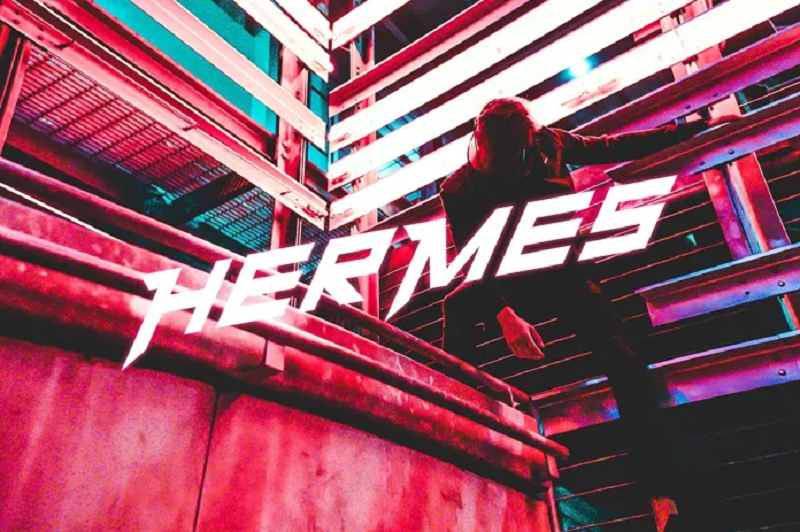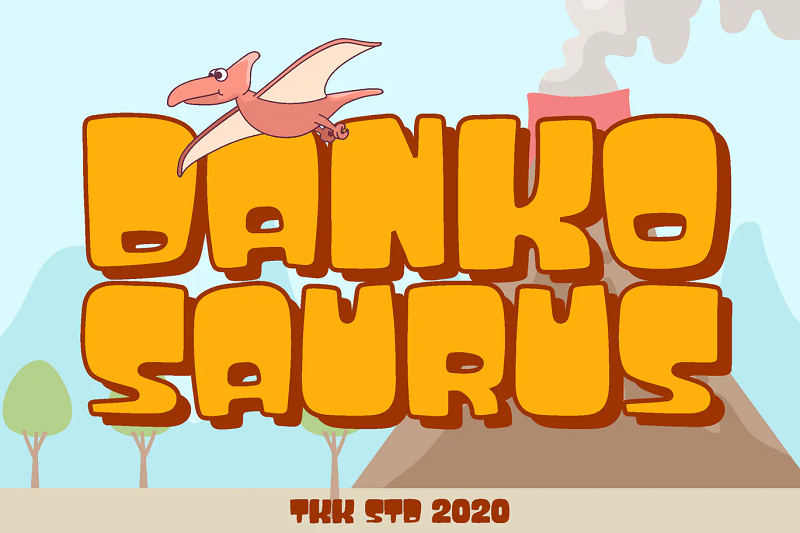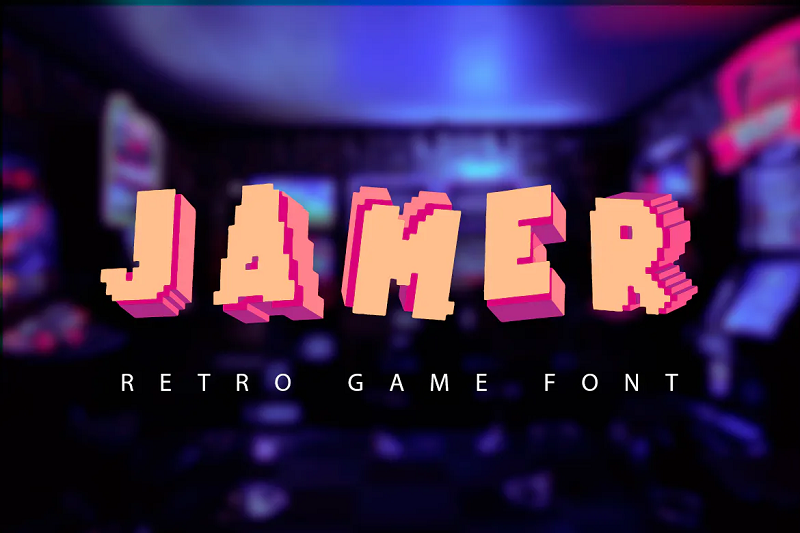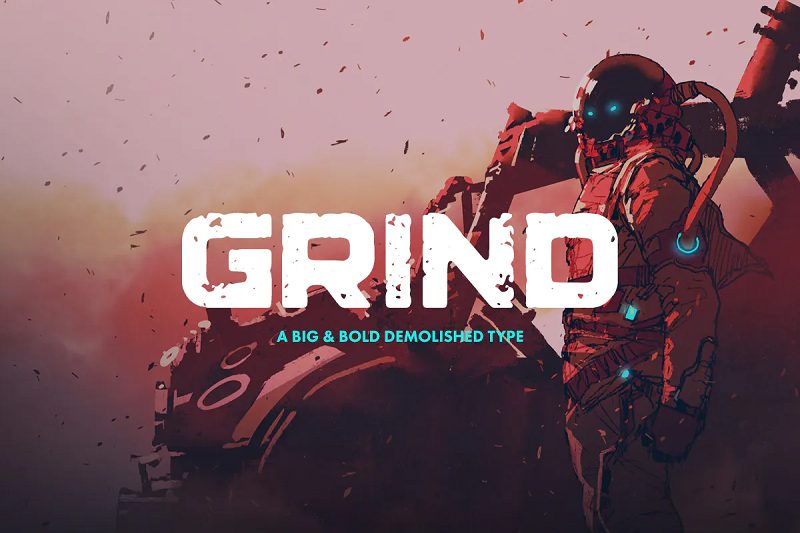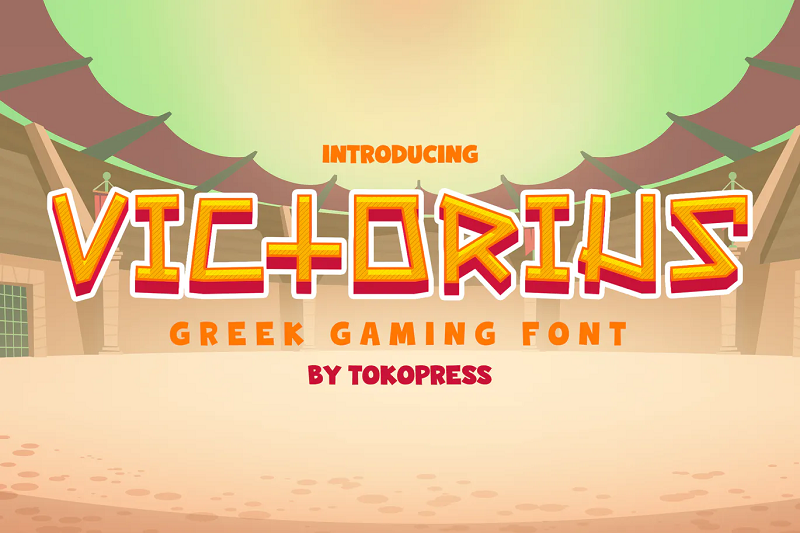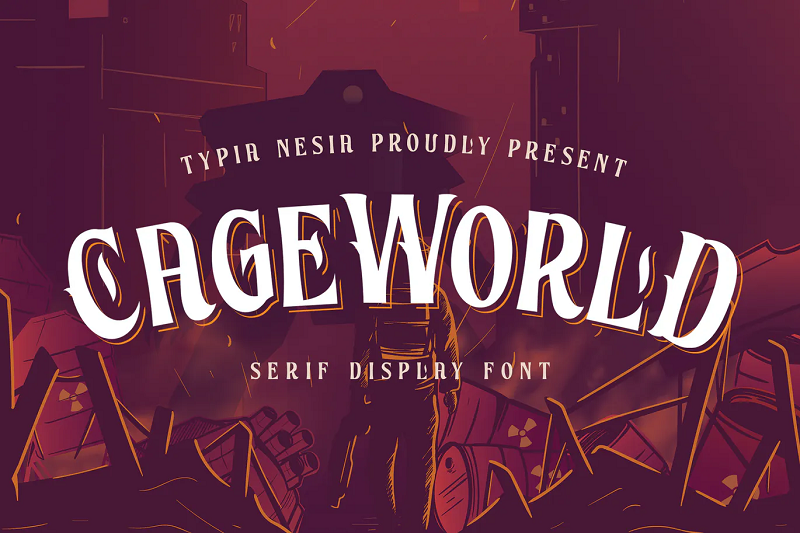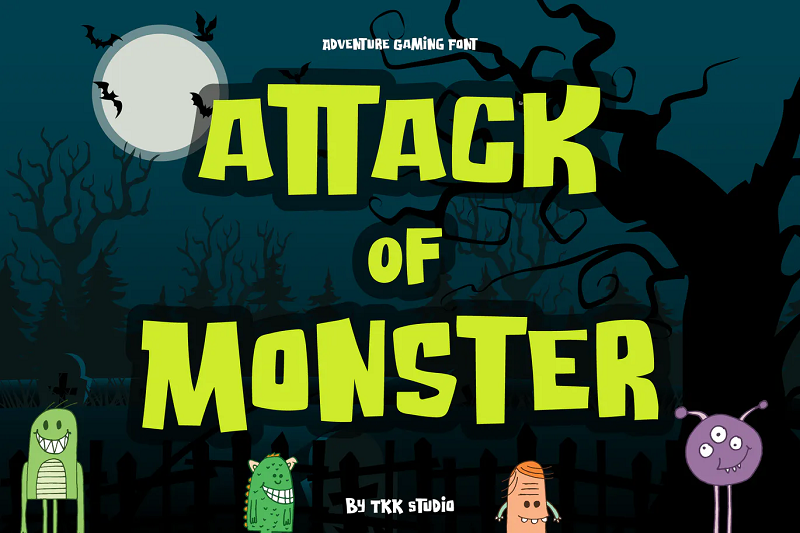
40 Font Game Terbaik Untuk Semua Desain Terkait Game Anda (2023)
Diterbitkan: 2023-01-03Seperti yang kita semua tahu, gamer memiliki selera gaya artistik yang unik. Jika Anda ingin memanfaatkan estetika permainan itu dan membuatnya kembali dalam proyek kreatif Anda sendiri, Anda memerlukan font yang tepat untuk pekerjaan itu.
Dengan mengingat hal itu, kami telah menyusun daftar font game terbaik yang tersedia pada tahun 2021. Tipografi di bawah ini cocok untuk desain terkait game apa pun.
Apakah Anda seorang pengembang video game yang mencari font keren untuk digunakan dalam proyek terbaru Anda, seorang pemasar yang mengerjakan branding/materi promosi game, atau streamer Twitch/pemain game YouTube yang mencari jenis huruf menarik untuk digunakan dalam sampul saluran Anda, Anda Anda pasti akan menemukan font yang Anda sukai di daftar ini.
40 font game terbaik
1. Font Permainan Video
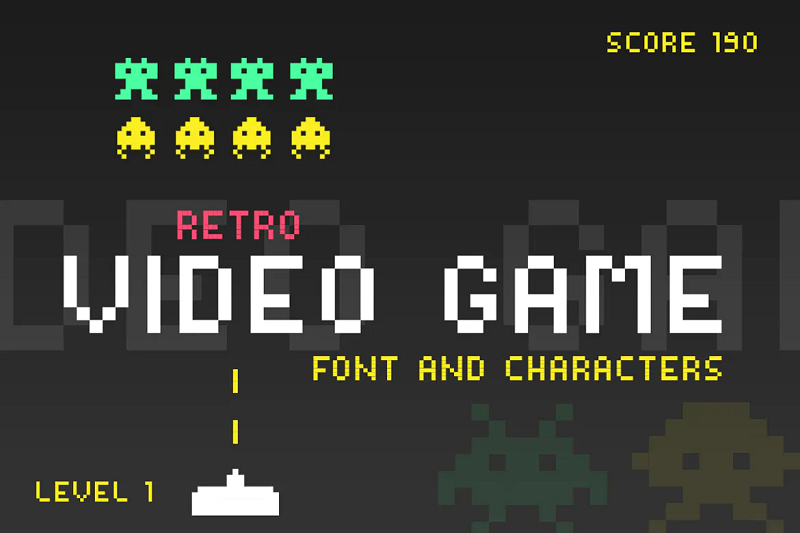
Mari kita mulai dengan ledakan ke masa lalu dengan 'font video game' yang terinspirasi gaya retro. Ini adalah desain yang memberi penghormatan pada game arcade klasik seperti penembak Mars favorit semua orang dari tahun 80-an, penyerbu luar angkasa. Ini sangat nostalgia.
Ini memiliki desain pixelated dan unduhan dilengkapi dengan set karakter utama dan 17 bonus pixelated martians, sehingga Anda dapat menambahkan beberapa grafik 8-bit yang keren ke desain Anda.
2. Jenis Huruf Tsuki
Tsuki adalah salah satu font sans-serif favorit pribadi saya sepanjang masa. Jenis huruf yang indah ini penuh dengan karakter. Ini terinspirasi oleh Manga Jepang dan akan terlihat bagus di JRPG dan game indie.
3. Game Over Font
Game Over adalah kuas buatan tangan dan font SVG. Desain sapuan kuas itu akan terlihat bagus dalam game horor, grunge, dan proyek artistik lainnya. Seperti namanya, itu juga akan berfungsi dengan baik sebagai teks 'game over' dalam game.
4. GUMDROP
Gumdrop adalah font yang menyenangkan, unik, dan modern yang bagus untuk game seluler. Ini adalah font kotak-kotak yang melompat dari halaman, sehingga akan bekerja dengan baik pada judul, poster, ikon YouTube, logo aplikasi android/ios, dan banyak lagi. Set termasuk karakter AZ dasar dalam huruf besar dan kecil, angka, dan tanda baca. Ini sepenuhnya kompatibel dengan Adobe Illustrator dan Photoshop.
5. Font Permainan Caveman
Seperti namanya, Caveman adalah font yang sepertinya berasal dari periode paleolitik. Ini sempurna untuk judul game bertahan hidup dan game apa pun yang dibuat di era kuno / Jurassic. Ini adalah jenis huruf yang kuat dan menarik yang terlihat seperti dipotong langsung dari lempengan batu.
6. Font Game Starzone Scifi
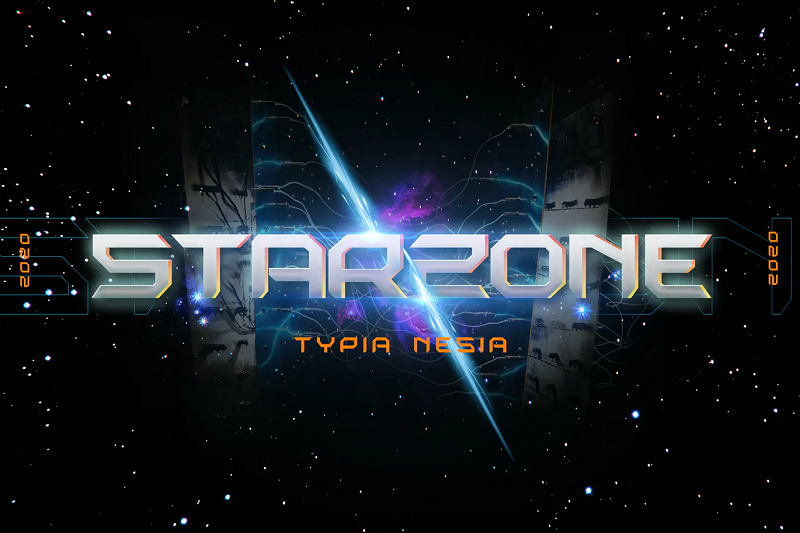
Jika Anda sedang mencari font futuristik untuk permainan scifi, tidak terlihat lagi dari Starzone. Ini adalah font robot yang dirancang secara profesional yang terlihat bagus di poster scifi, branding video game, pengemasan produk, dan banyak lagi.
7. Font game balap monocoque
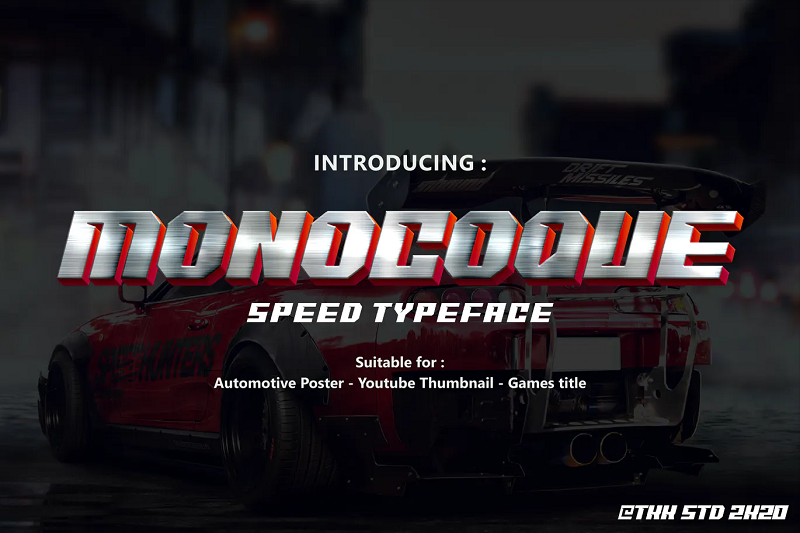
Monocoque adalah 'jenis huruf kecepatan' dengan bentuk kuning dan sudut tajam. Ini dengan sempurna menangkap esensi kecepatan, dengan karakter yang condong ke depan seolah-olah berlari keluar dari halaman. Ini membuatnya cocok untuk game mobil dan game balapan.
8. Permen Jambu
Game seluler bertema permen sangat populer akhir-akhir ini. Jika Anda sedang mengerjakan proyek desain untuk sesuatu yang serupa, jenis huruf permainan anak-anak Guava Candy mungkin hanya font yang Anda cari. Ini adalah font yang menyenangkan, terinspirasi oleh kembang gula dengan desain yang melompat dari halaman. Estetika yang menarik perhatian membuatnya ideal untuk game seluler dan mini-game online.
9. Petualang Sungai
River Adventurer adalah font yang sempurna untuk game petualangan. Ini adalah font game sans-serif kotak-kotak dengan huruf besar semua yang mengingatkan kita pada hutan dan gambar satwa liar. Ini benar-benar membangkitkan rasa petualangan dan akan sempurna untuk desain yang menarik di mana Anda ingin teksnya benar-benar menonjol, seperti logo app store, poster, dan gambar mini Youtube.
Pikiran terakhir
Itu dia – 40 font game terbaik di tahun 2023 untuk menginspirasi proyek kreatif Anda berikutnya. Jika Anda masih belum menemukan font yang Anda cari, lihat koleksi font fantastis ini untuk mendapatkan lebih banyak ide!